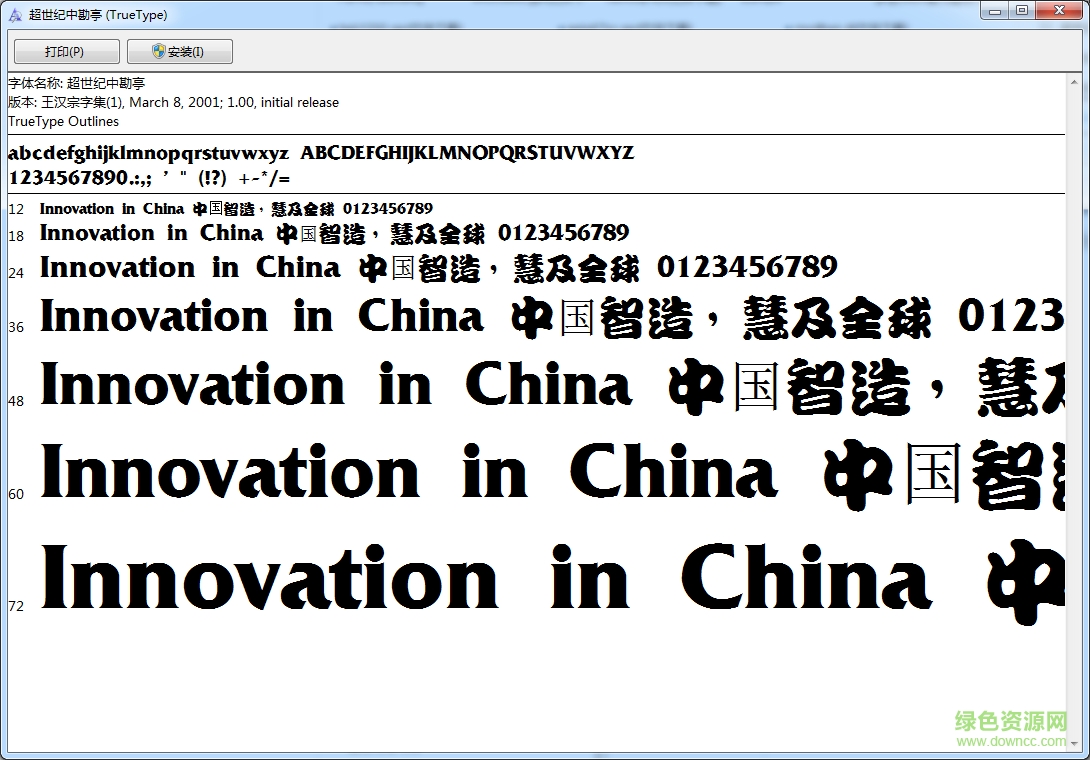
超世紀(jì)中勘亭字體是一款非常有個性的電腦字體軟件,字體風(fēng)格簡潔突出重點,字體看起來十分的簡單大方,而且打印排版看起來也是非常的不錯,快速安裝即刻使用。來綠色資源網(wǎng)下載體驗吧!
超世紀(jì)中勘亭體繁是一款應(yīng)用于設(shè)計方面的繁體中文漢字,字體端正大方,飄逸清秀,適用于廣告設(shè)計、平面設(shè)計、創(chuàng)意創(chuàng)作、印刷包裝、正文標(biāo)題等領(lǐng)域,喜歡的網(wǎng)友可免費下載收藏。